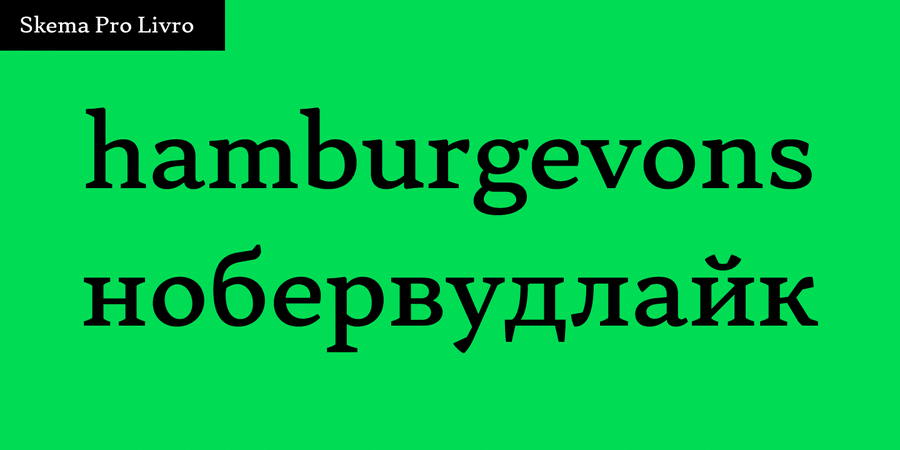
Опис гарнітури Skema Pro Livro – слабоконтрастна гарнітура з низькими рядковими та нахиленою віссю контрасту. Основне використання – книги, де довгі виносні елементи і збільшена межрядкова відстань сприяють читанню.
Skema Pro – система з 6 антикв, кожна з яких має свій характер і призначення. Разом вони формують величезну супергарнітуру з 84 накреслень для будь-яких можливих завдань.
Сімейство Skema Pro розробив і випустив Андрій Константинов у студії Mint Type у 2017 році.
Асоціації з сімейством шрифтів Skema Pro LivroОсобистість і характер гарнітури:
тонкий, легкий, делікатний, спокійний, рівний, гармонійний, врівноважений, космополітичний, ненав'язливий, технічний, сучасний, точний, логічний, непомітний, культурний, освічений, серйозний, твердий, динамічний, худий, якісний, ввічливий, зрозумілий, нейтральний, середній, звичайний, помірний, доступний, стійкий, комфортний, зручний, гуманітарний, комільфо, благородний, консервативний, традиційний, класичний, архітектурний, тактичний, формальний, універсальний, діловий, практичний, оптимальний, розумний, стабільний, міський, переконливий, пафосний, солідний, авторитетний, відповідальний, значний, суворий, міцний
Місто, література, освіта, культура, бібліотека, мистецтво, музей, проза, архітектура, історія, скульптура, наука, суспільство, юрист, адвокат, фінанси, правосуддя, економіка, бізнес, банк, суд Гарнітура асоціюється з віком: